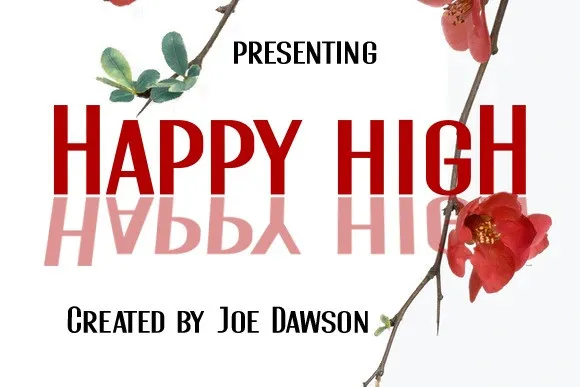
Happy High Font
Esta é uma família de fontes sans-serif que se destaca por sua simplicidade e modernidade. Ela foi criada pelo designer Joe Dawson, reconhecido por suas habilidades excepcionais na criação de tipo para uso em ambientes visuais impactantes. A “Happy High Font” tem um design simples e elegante que permite seus usuários criar projetos inspiradores e distantes. Com a capacidade de transformar qualquer projeto em algo único e vanguardista, esta fonte se destaca como uma opção ideal para quem busca dar vida criativa e visionária aos seus conceitos inovadores. Seja para aplicações digitais ou impressas, essa família de fontes certamente fará sua marca no seu trabalho, oferecendo a praticidade que você precisa com um estilo único e moderno.